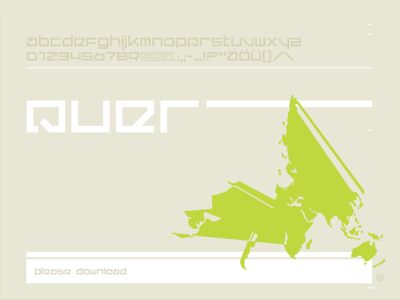
Quer Regular 字体
Quer Regular
由 Onezero 设计的 Quer Regular 是一款免费的未来感标题字体,具有硬朗的模块化节奏和独特的早期数字时代风格。字母由块状直角和截断的斜线构成,这使得大写字母呈现出一种机械感和神秘感,而非流畅圆润的风格。
这使其成为科幻海报、游戏 Logo、专辑封面、标题卡以及小型品牌系统的理想选择——当免费字体需要在寥寥数语中传达出强烈的科技感时,它尤为出众。它在短文本应用中效果最佳,例如标题、封面文案、字母组合以及具有界面设计感的商标,其方形的切角和缺失的角落赋予了每一个词汇一种如同代码般的信号感。